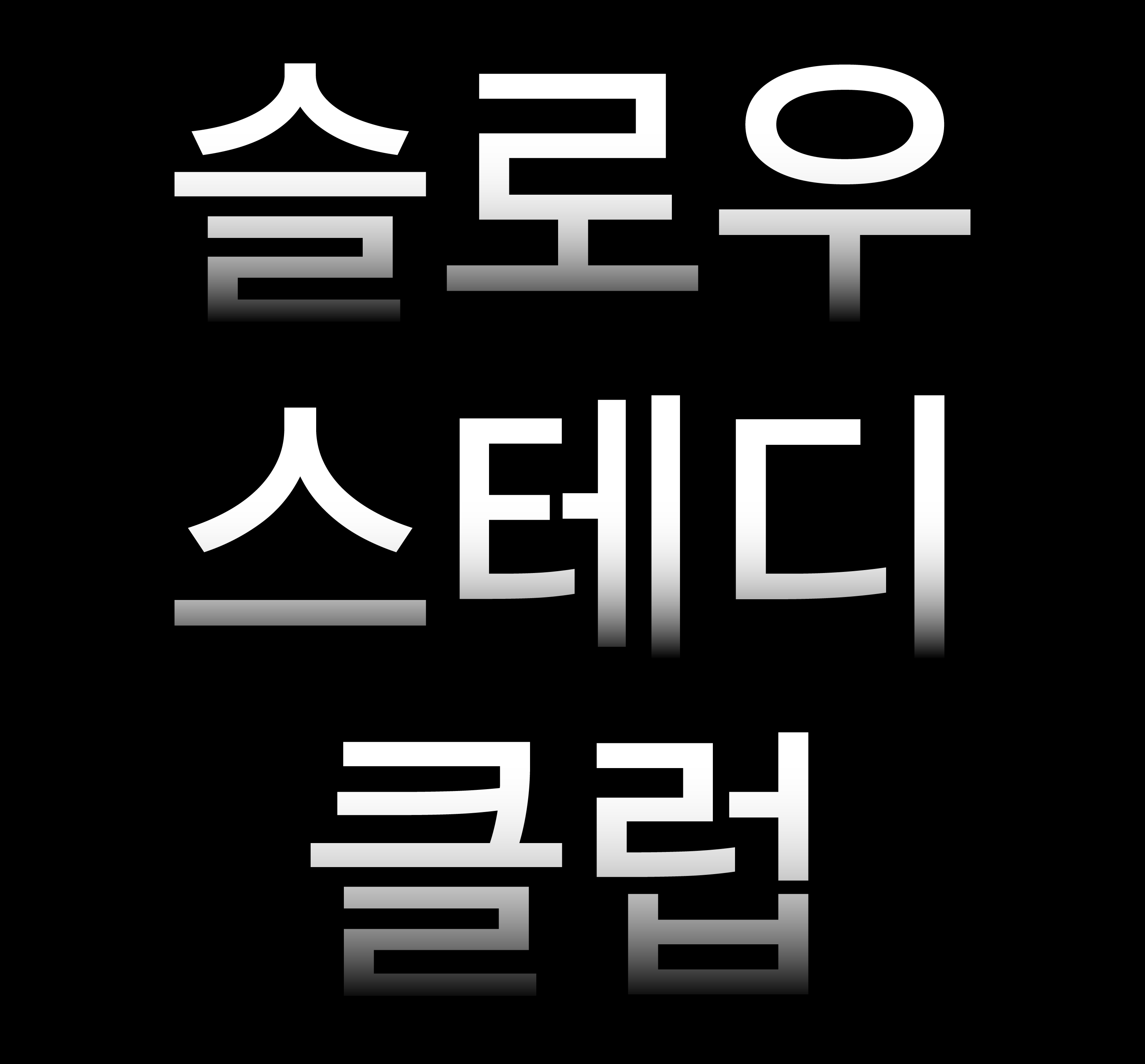
[헤드라인]슬로우스테디클럽
Yoon 슬로우스테디클럽
모든 게 빠르게 변화하는 현대 사회, 시간이 흘러도 변치 않을 가치 있는 것들을 셀렉하여 소개하는 편집숍 슬로우스테디클럽의 전용서체입니다. 윤고딕100번대를 재해석해 더욱 세련되어진 모습으로 Basic & Sustainable의 가치를 전달합니다.
현재까지도 수많은 디자이너에게 영감을 주고 있는 BRAUN의 수석 디자이너 디터 람스는 ‘Less But Better (필요 없는 것을 없애고, 필요한 것에 집중하는 것).’라는 디자인 철학을 강조했다. 디터람스의 이러한 디자인 철학은 최정호원도를 기반으로 한 기존 고딕 서체에서 불필요한 세리프와 돌기를 정리한 ‘윤고딕’, 그리고 ‘슬로우스테디클럽’의 브랜드 철학과도 일치한다고 볼 수 있다. 슬로우스테디클럽은 불필요한 요소를 제거한 베이식한 디자인과 지속가능성, 그리고 본질적이고 실용적인 가치를 중심으로 패션과 라이프스타일 소품을 소개하는 브랜드이다. 이전부터 슬로우스테디클럽은 윤고딕을 브랜드 전반으로 사용해왔으나, 다양한 방면으로 확장해가는 슬로우스테디클럽 브랜드만의 철학과 메시지를 전달할 수 있는 커뮤니케이션 툴(서체)이 필요했다. 슬로우스테디클럽 서체는 지속가능성과 스테디함을 가진 윤고딕의 DNA를 계승하며, 그 안에서 윤고딕과 슬로우스테디클럽의 교집합을 찾아, 사용성을 중심으로 발전된 사용환경과 시대 흐름에 맞게 업그레이드하였다.
Straight
기존 윤고딕 한글 자소와 영문, 숫자, 기호에 직선적인 요소를 담아 글자의 인상을 명료하게 바꾸어 주었다. 획의 꺾임과 마무리를 더욱 힘 있고 단정하게 조정하여 화면과 지면, 그리고 작은 크기에서도 획이 일그러지지 않고 정확하게 보이며, 이는 슬로우스테디클럽의 꾸준하고 일관성 있는 아이덴티티를 나타낸다.
Space
한글 자소의 폭을 키워 공간을 채워주며, 전체적인 ‘ㅇ’곡선의 텐션을 늘려줌으로 글자 전체적으로 여유로움을 주었다. 또 영문과 세로모임 민글자의 높이를 더 채워주어 크기감을 맞추고 조판 시 글줄의 흐름을 좀 더 안정적으로 가져가게 하였다.
Less
현대적인 인상에 맞게 한글의 자간감과 장평이 조정됨으로 기존 윤고딕의 넓어 보이는 한글 장평의 문제를 해결하고 짜임새 있으며 긴 글의 조판 시에도 용이하게 하였다. ‘ㄱ, ㅅ, ㅈ’ 등의 획에서 보이는 삐침의 각도를 조정해 기존의 올드한 획의 인상을 바꾸어 주었다.
Usability
조판 시 한글과 영문, 기호 간의 관계 정리와 통일감을 맞추는 작업이 있었다. 베이스라인을 기준으로 한 전체적인 글줄의 맞춤과 높이, 한글에 비해 얇은 영문의 두께가 미세하게 조정되었다. ‘?, !, +, -, ~’ 등의 기호에서 크기감과 자간감이 수정되었다.
Latin
기존 윤고딕의 영문에서 전체적인 회색도 정리와 곡선감 등 완성도적인 부분에서의 작업이 있었다. ‘g, p’ 등에서의 짧은 디센더 길이를 확보해주며, 이와같이 ‘h, d’ 등에서의 어센더 길이를 확보해주어 안정적인 영문의 형태를 가져갔다. ‘f, t’ 등에서의 짧은 획 표현 또한 확실히 해주어 판독성과 가독성을 높였다.
Laundry symbol
사용자영역 글립에 자주 사용하는 32개의 세탁기호를 추가해 서체와 같이 사용할 수 있게 하였다.